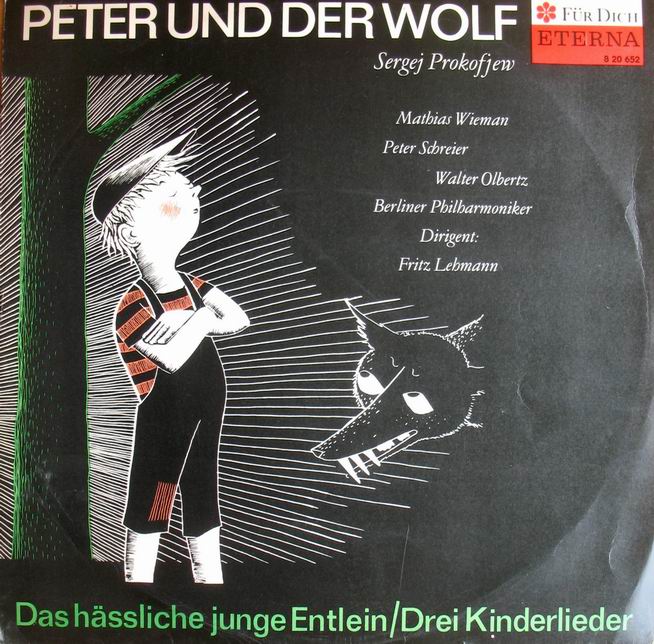
Schrift zu Prokofjew
Ich bitte um euren Rat - für das Cover von "Peter und der Wolf" von Sergej Prokofjew suche ich eine passende Schrift. So richtig kann ich mich nicht entscheiden. Einfliessen sollten folgende Stichpunkte:
- es ist ein Werk für Kinder
- Prokofjew wechselte zu dieser Zeit von Frankreich in die Sowjetunion
- 1936
Es soll schnell und eindeutig wahrgenommen werden, kann aber sehr wohl eine originelle Schrift sein.
Auf dem Titel gibt es farbige Zeichnungen.
Cover wovon? CD? Notenausgabe? Was für eine Notenausgabe? Klavierband für Kinder? Partitur? Wer genau gehört zur Zielgruppe des Produkts?
Was Du als Stichpunkte beschreibst, ist ein ganz enormer Spagat. Prokofjew hat Rußland verlassen weil im politischen Klima der Zeit die Leute mit seiner experimentellen Musik nicht viel anfangen konnten. In Amerika ist das nicht so viel besser gewesen; die Pariser Konzertbesucher scheinen da offener gewesen zu sein. Trotzdem hat es ihn in seine Heimat zurückgezogen. Das könnte man typografisch verwerten, ob es mich aber als Käufer reizt ist ja schon wieder eine ganz andere Frage. Man kann eine Schrift der Zeit aufgreifen; die hat dann aber vermutlich wenig damit zu tun, daß es sich um ein Werk für Kinder handelt.
Ich habe durch Zufall eben ein Bild des Covers einer Schallplatte gefunden, welche ich als Kind gehört habe. Die Typografie wurde hier einfach relativ neutral gehalten. Die Abbildung hingegen hebt hervor, daß es sich um ein Werk für Kinder handelt. Man mag sich über die Gestaltung der Platte streiten, ich bin halt damit groß geworden. Ich finde sie aber trotzdem ansprechender als z.B. das Cover dieser Klavierausgabe, aus welcher ich mal gespielt habe. Das konnte ich als Jugendlicher nicht leiden und kann es heute immer noch nicht.
Ein ganz anderer Weg wurde hingegen hier gewählt, wo die Ausführenden im Vordergrund stehen. Eine meiner Lieblings-Aufnahmen; Sean Connery ist einfach schwer zu schlagen. :wink:
Ich persönlich würde ja sowas gut finden, also Individualisierung durch die Handschrift/Unterschrift von Prokofjew, dazu aber eine relativ neutrale Schrift. Die Kindertauglichkeit kommt dann mit der Illustration. Das ist aber meine persönliche Meinung. :D
Zunächst einmal - es ist meine eigene Bearbeitung siehe hier:
Die Musik ist für Kinder zum hören, gespielt wird sie aber von höchst professionellen Musikern. Und die sollen mit angesprochen werden. Die Zeichnungen habe ich auch mit angefertigt.
Das es ein Spagat ist wird mir auch bewusst, deswegen der Hilferuf!
Prokofjew hatte in der Sowjetunion ab 1927 unglaublichen Erfolg. Das war wohl der Hauptgrund in seine Heimat wieder zu ziehen. Ab 1937 durfte er dann gar nicht mehr Reisen.
Tja - aber auch viele seiner besten Werke entstanden in dieser Zeit. Auch ein Spagat.
Und die Zeichnungen des Buches (und der Schallplatte) sind natürlich legendär und auch feste Bestandteil meiner Kindheit.
Ich habe durch Zufall eben ein Bild des Covers einer Schallplatte gefunden, welche ich als Kind gehört habe.
:cheer: Die habe ich auch als Kind gehört – und auf der Hülle eine echte Klemke-Zeichnung.
>> Robert: Versuch doch mal die Fontin: Da gibt es eine Sans und eine Serif, ziemlich weich und sehr anpassungsfähig. Das sind sogar Freefonts und irgendjemand hier kann Dir bestimmt sagen, wo Du die findest. Nur das Kerning wirst Du manuell anpassen müssen, das ist nicht so super; aber für ein Cover geht das schon mal. Auf den historischen Bezug würde ich mich nicht unbedingt versteifen; das wäre ein ziemlich weites Feld und der Rezipient nimmt es am Ende doch nicht wahr. Das mit der Fontin ist auch mehr so aus dem Bauch; frag also bitte nicht warum. Scheint mir einfach zu der Musik und den Bildern zu passen.
Werde ich gerne ausprobieren. Übrigens um mal eine Korinthe hier abzulassen - es ist keine Klemke-Zeichnung sondern von Frans Haacken :D
p's musik mag zu seiner zeit als experimentell wahrgenommen worden sein – gerade »peter und der wolf« ist aber heute eher musikalischer mainstream (ganz anders als bei schostakowitsch, dessen musik sehr viel stärker biografische, historische und soziale bezüge hat und bei dem es sich dann und wann anbietet, konstruktivistische – eigentlich: suprematistische – einflüsse einzubeziehen). hier muss die schrift ja vor allem mit den illustrationen harmonieren.
also. mein vorschlag dazu – ganz subjektiv: ff tisa (aber nicht kostenlos). viel auswahl: unter 20 schnitten wird sich doch was finden lassen ...
Die Illustrationen sprechen mich spontan sofort an. Sie verknüpfen aber den Inhalt des Werkes mit der Musik – und genau das finde ich auch richtig! :biglove:
Da haben dann aber die biografischen Informationen zu Prokofjew im Grunde keinen Platz mehr. Entweder eine neutrale Schrift, die von der Illustration eher zurück tritt. Oder aber (und das paßt m.E. auch zum Stil der Illustrationen) eine gut gemachte, etwas verspieltere Schrift. Mir kommen hier spontan einige Schriften vom Lebedev Studio in Moskau in den Sinn (die »Neuch« ist vermutlich zu übertrieben, aber so etwas in der Richtung wie die »Heino« könnte ich mir ganz gut vorstellen; das müßte man aber mal ausprobieren). Da gibt es aber natürlich auch mehr und vielleicht noch etwas eleganteres.
Warum der Vogel allerdings nicht nur so weit weg sondern auch auf der Rückseite ist, verstehe ich immer noch nicht! :wink:
Der Vogel (also die Schrift) wäre auf dem Titel zu verwirrend, also gibt es diese hinten drauf. Ich habe es ausprobiert.
Der Schlenker darunter ist ein kleiner Hinweispfeil.
Englisch - Russisch deswegen, weil es den Namen Prokofjew in recht vielen Schreibweisen gibt. Es gibt sogar noch ein "Prokoffief" usw.
Der geklaute kleine Raketenpionier hat übrigens auch seinen Sinn, im russischen Originaltext schreibt Prokofjew vom Pionier Peter!!